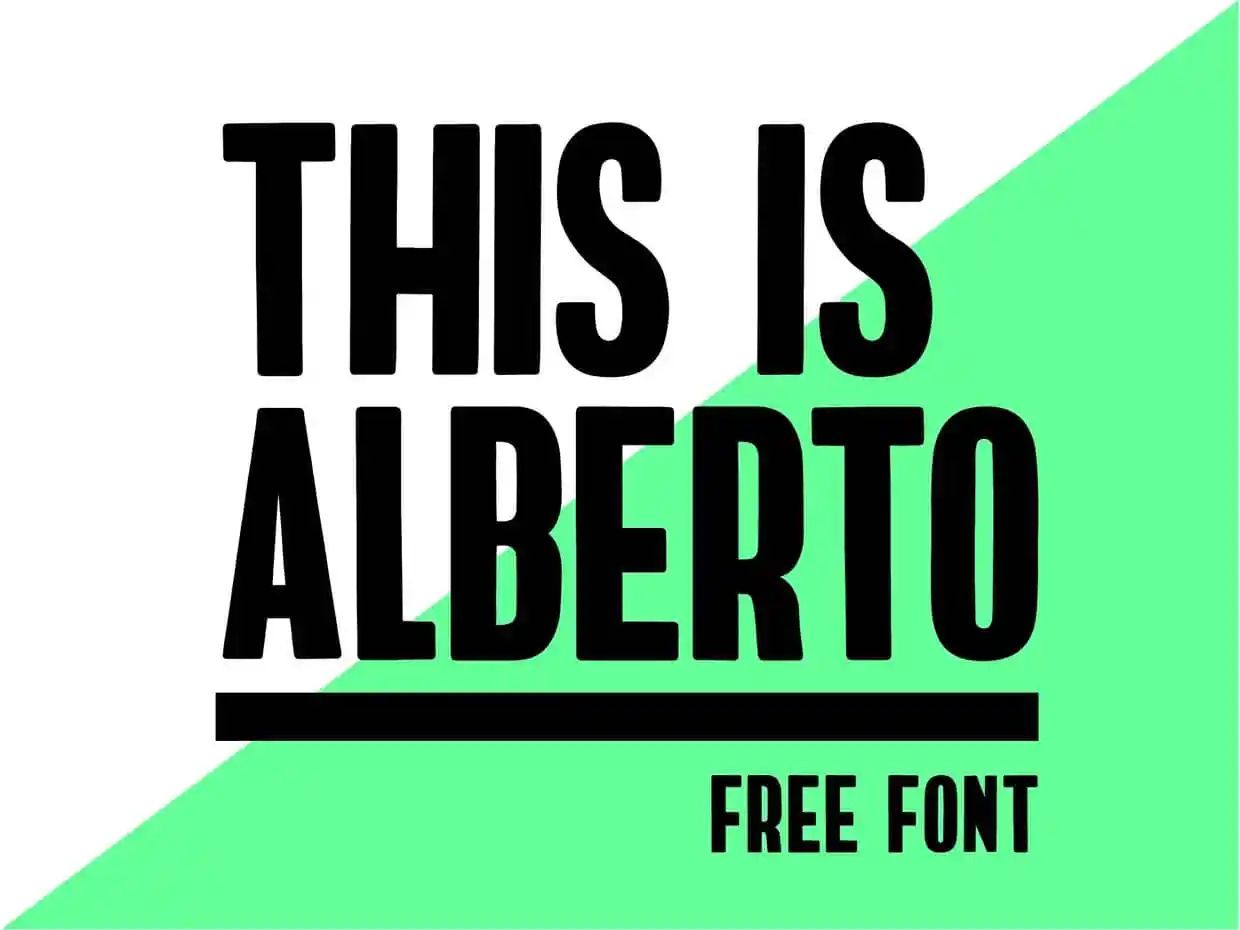
A fonte ALBERTO é uma escolha perfeita para designers que buscam uma tipografia moderna e despojada sem perder alegria, ideal para aplicativos digitais ou sites onde um estilo limpo e claro são fundamentais. Desenvolvida pelo designer Hamilton, essa fonte de tipo gorda traz uma combinação única de simplicidade e sofisticação. Suas linhas finas e os espaçamentos regulares garantem que seja fácil ler tanto em grandes tamanhos como em detalhes menores sem perder seu formato elegante e moderno. ALBERTO é perfeito para criar mensagens ativas e eficazes, proporcionando um contraste suave entre o texto e o fundo, tornando-a uma opção segura para qualquer aplicação digital que deseje transmitir sua ideia de maneira clara e envolvente.